「あ」のきれいな書き方
「あ」きれいに書けない!という方。
読みながら書いたら、
「あれ?きれいになってる⁇」
かもしれません。
「あ」の見本
こんな感じです。
「あ」のポイント
1画目
①右上がりに。短めにしましょう。
➁下に少し反ると◎です。
2画目
①中心からスタート。
➁少しふっくらさせて。
③中心よりもほんの少し左で終わります。←これ、重要です。
3画目
①1画目の右端よりも、少し内側から始めましょう。
➁1画目と下を揃えます。
③上に向かって折れます。
➃ここを一番高く。
➄45°くらいで、スッと払います。
➅ゆったりとした空間を作ると良いですね。
「あ」の外形
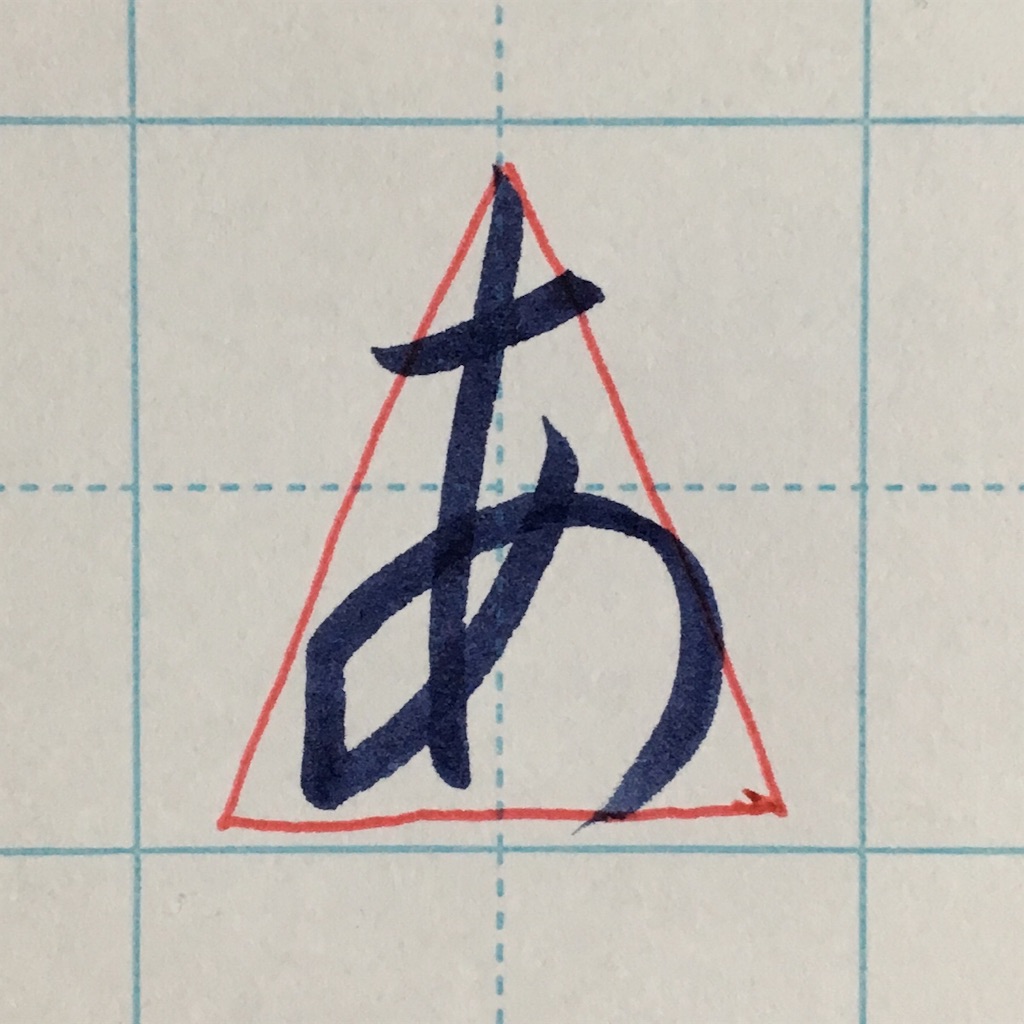
二等辺三角形になるように。
これはつまり、3画目の広げ方を左右同じくらいにする、ということです。
このバランスが崩れると、字が傾いてしまうので皆さんもぜひチェックしてみてください。
「あ」の字源と変遷
「安」という字から出来ています。
平安時代には、こんな感じで書かれていました。左はまだまだ漢字の要素が強いですね。
「あ」が上手く書けると気分が良いですね♩
練習はマス目を使うことをオススメします。無ければ、フリーハンドでもOK!